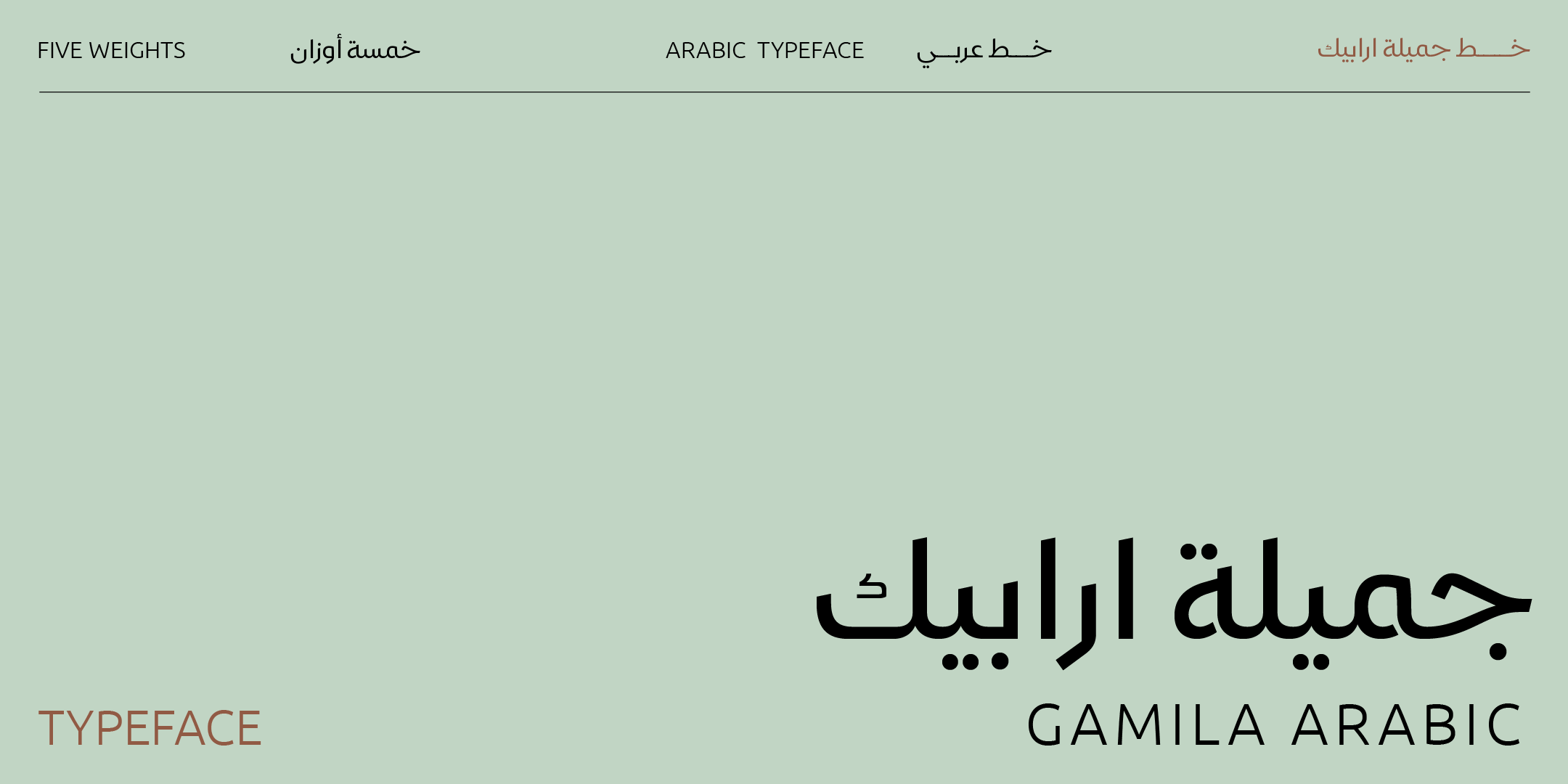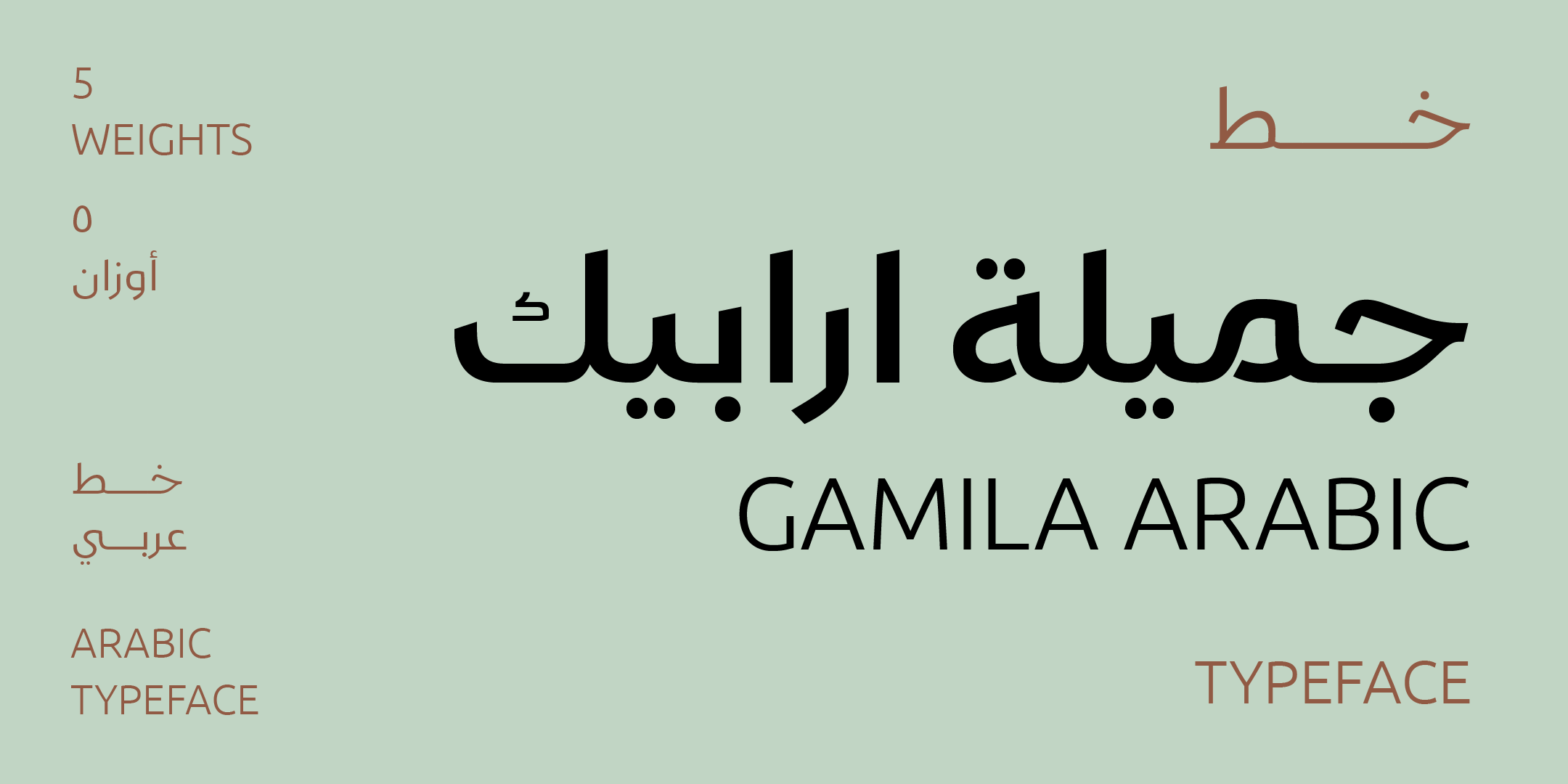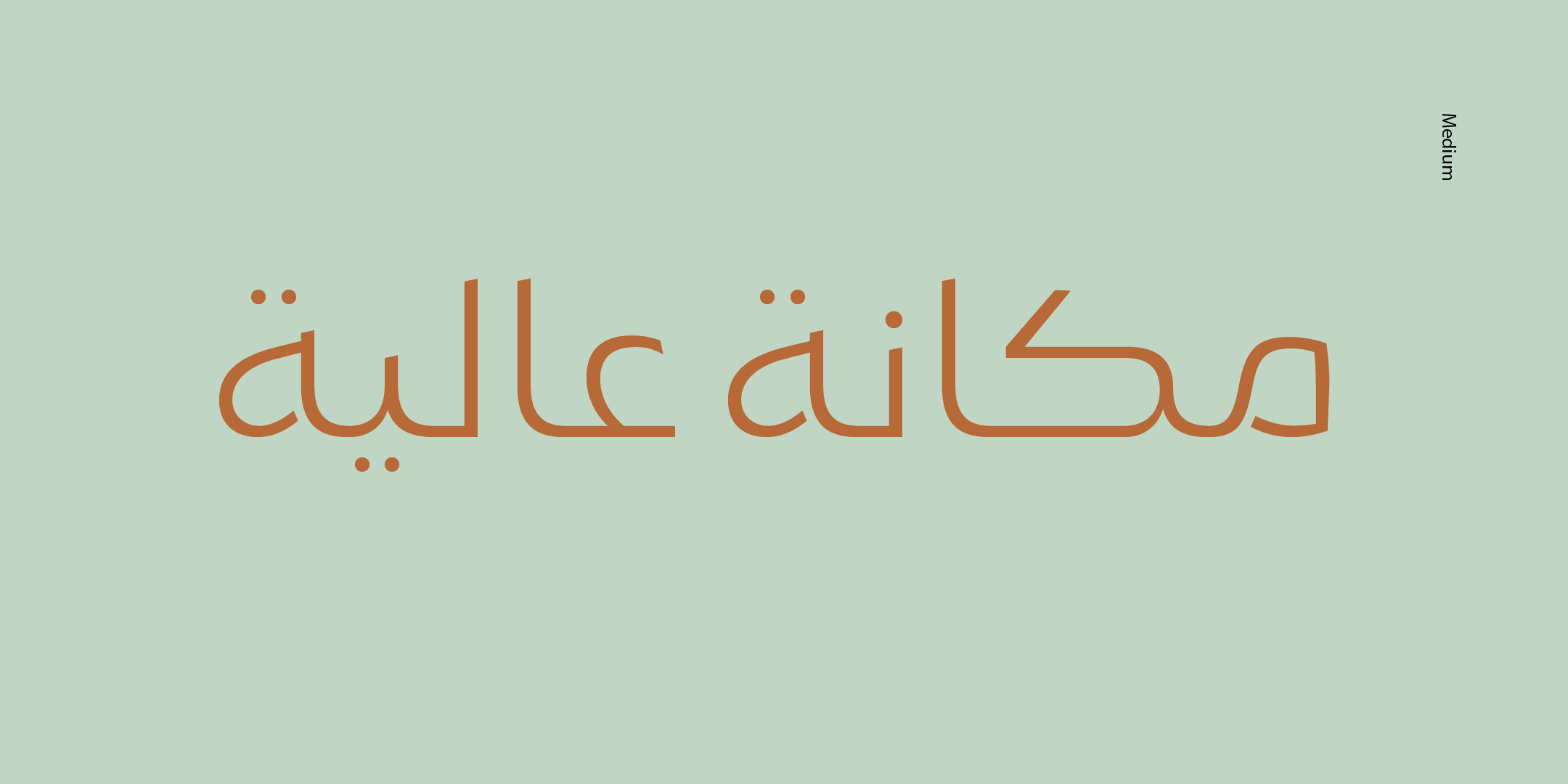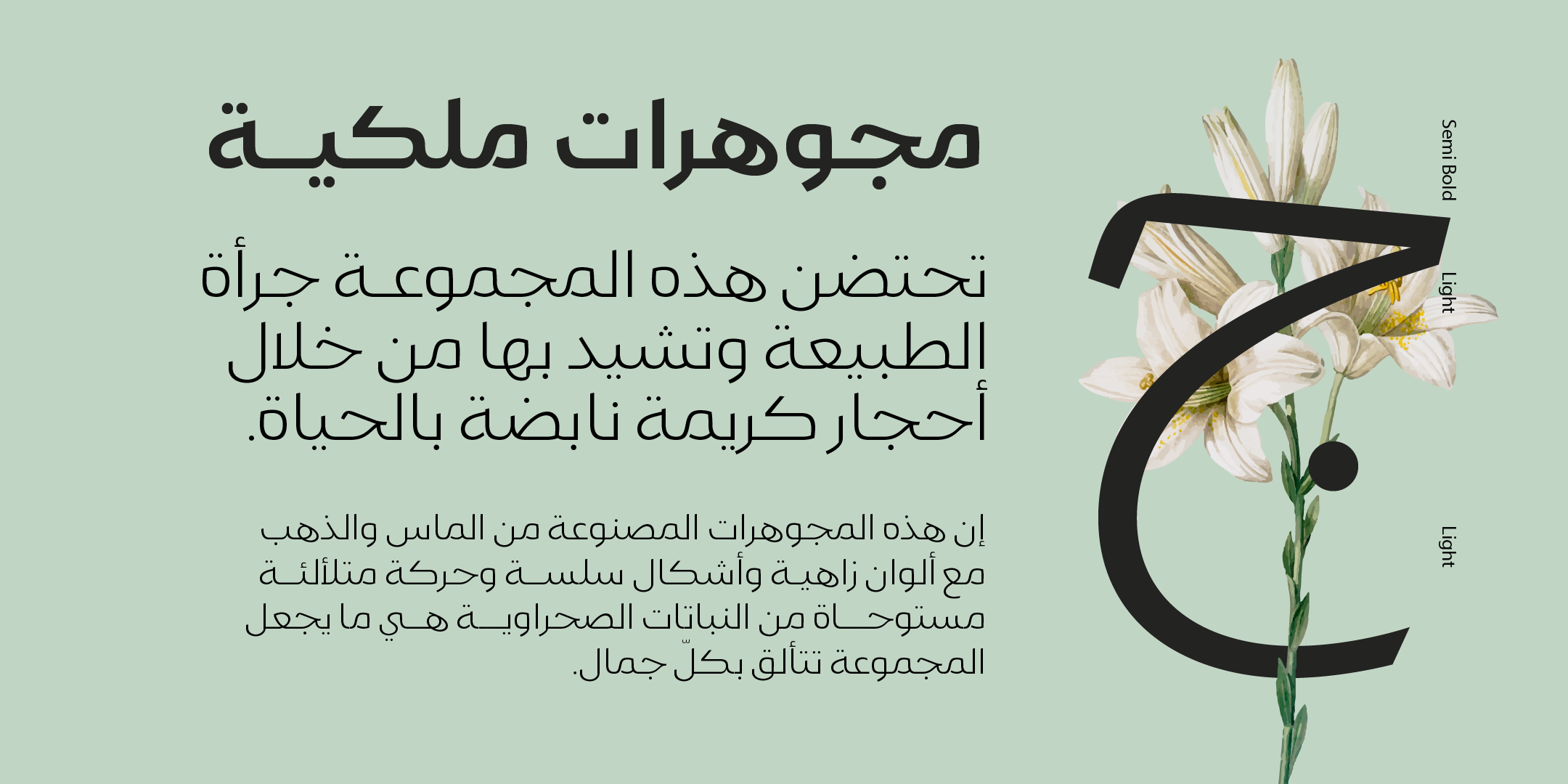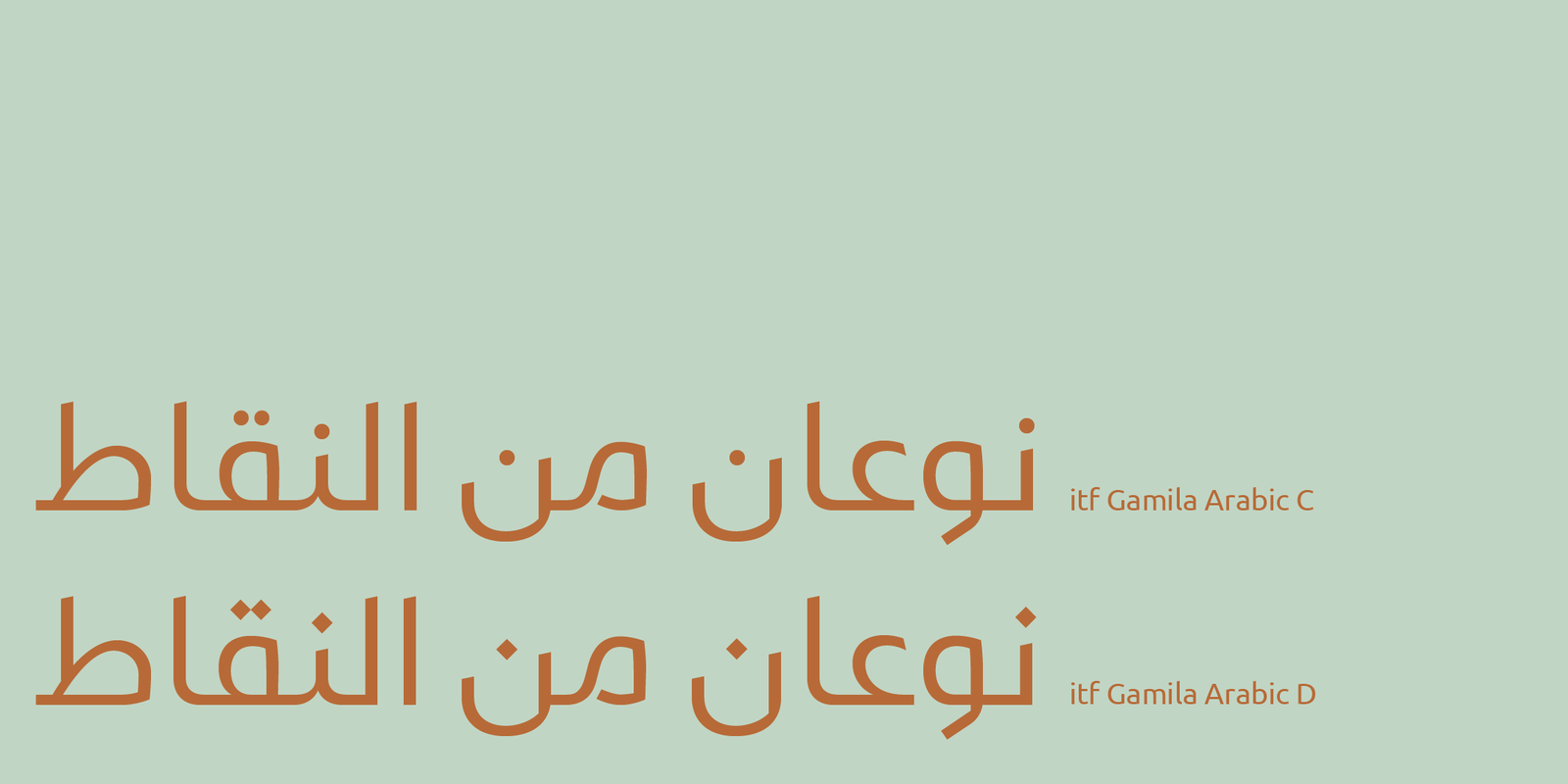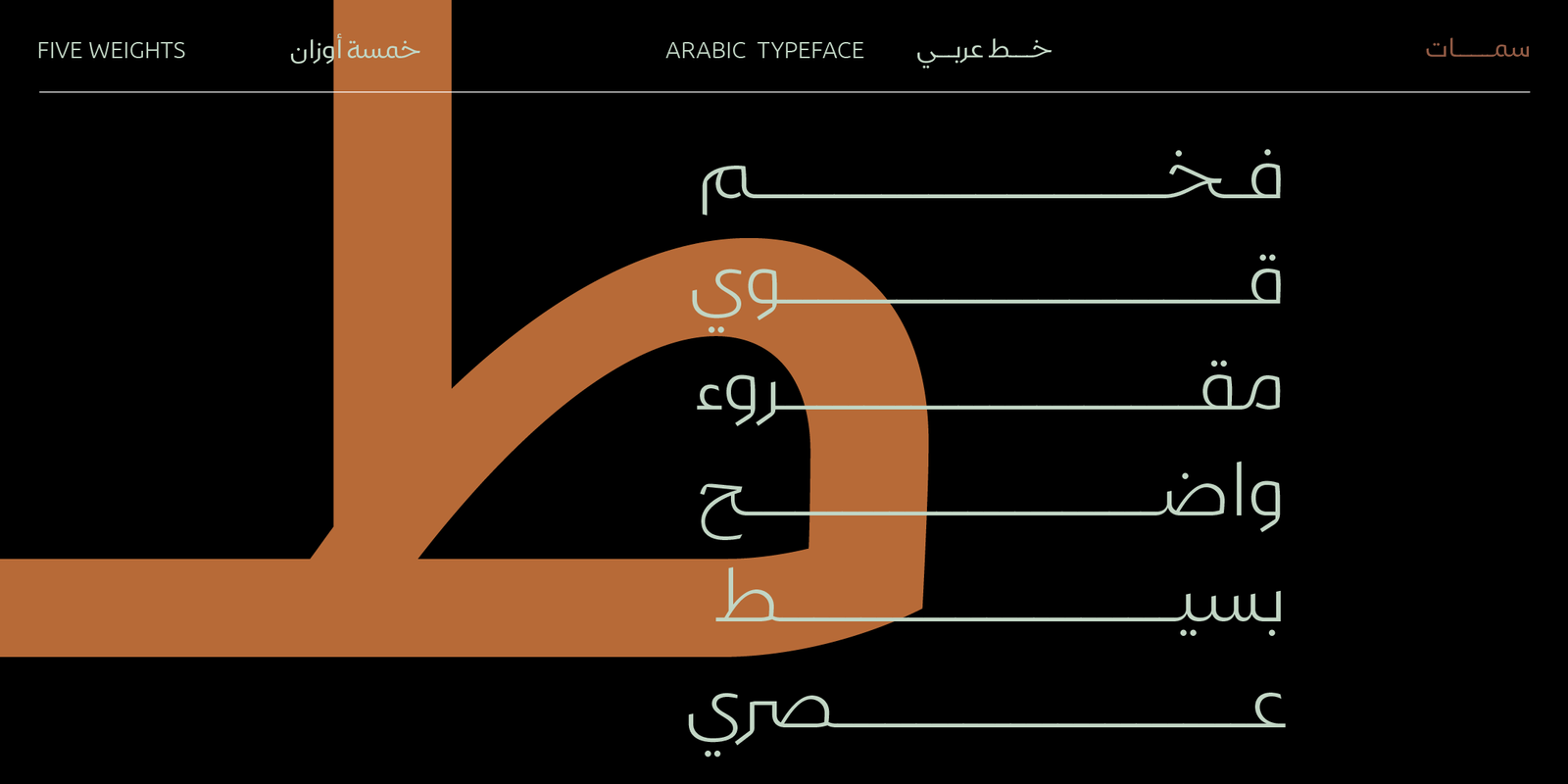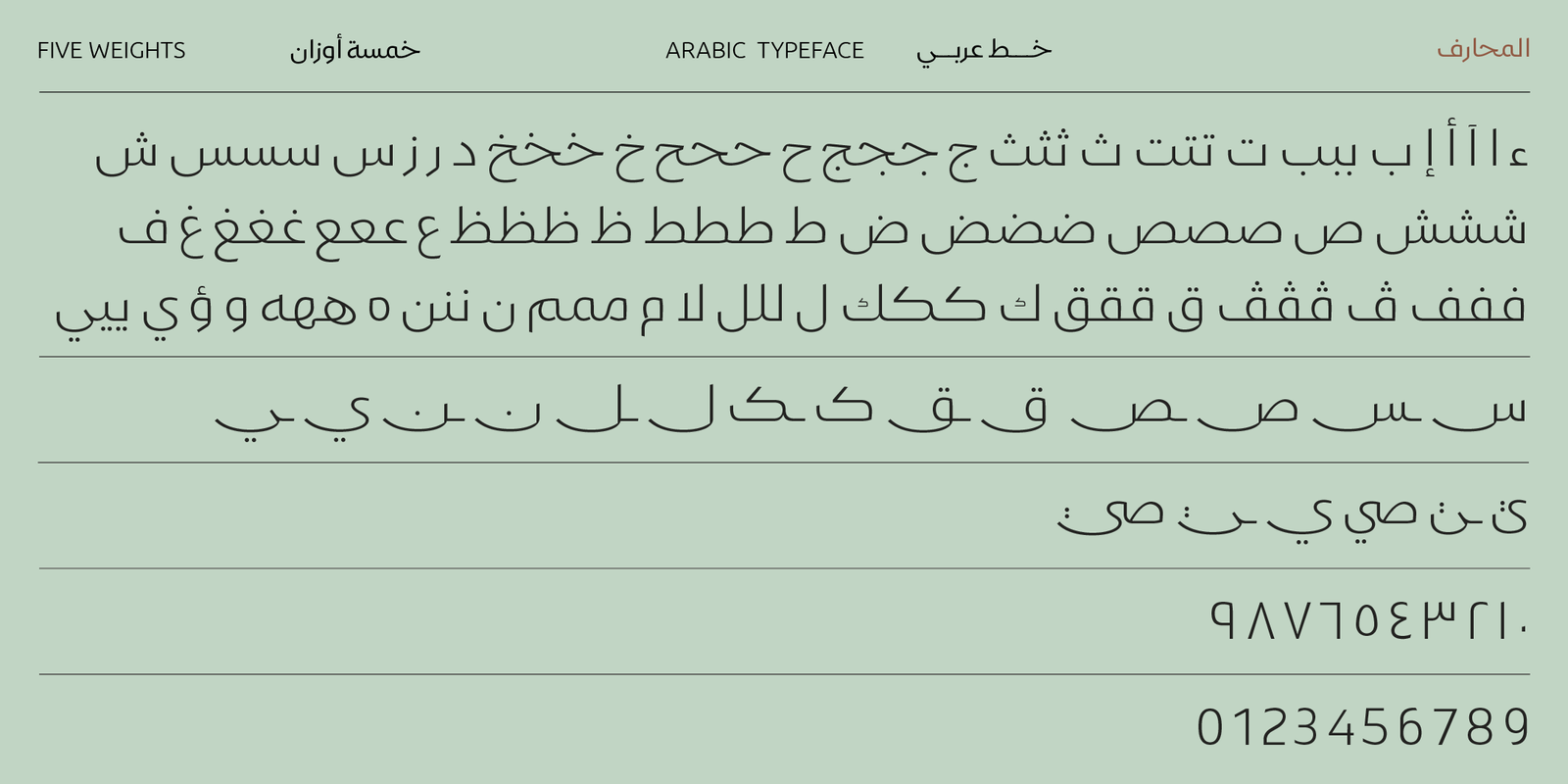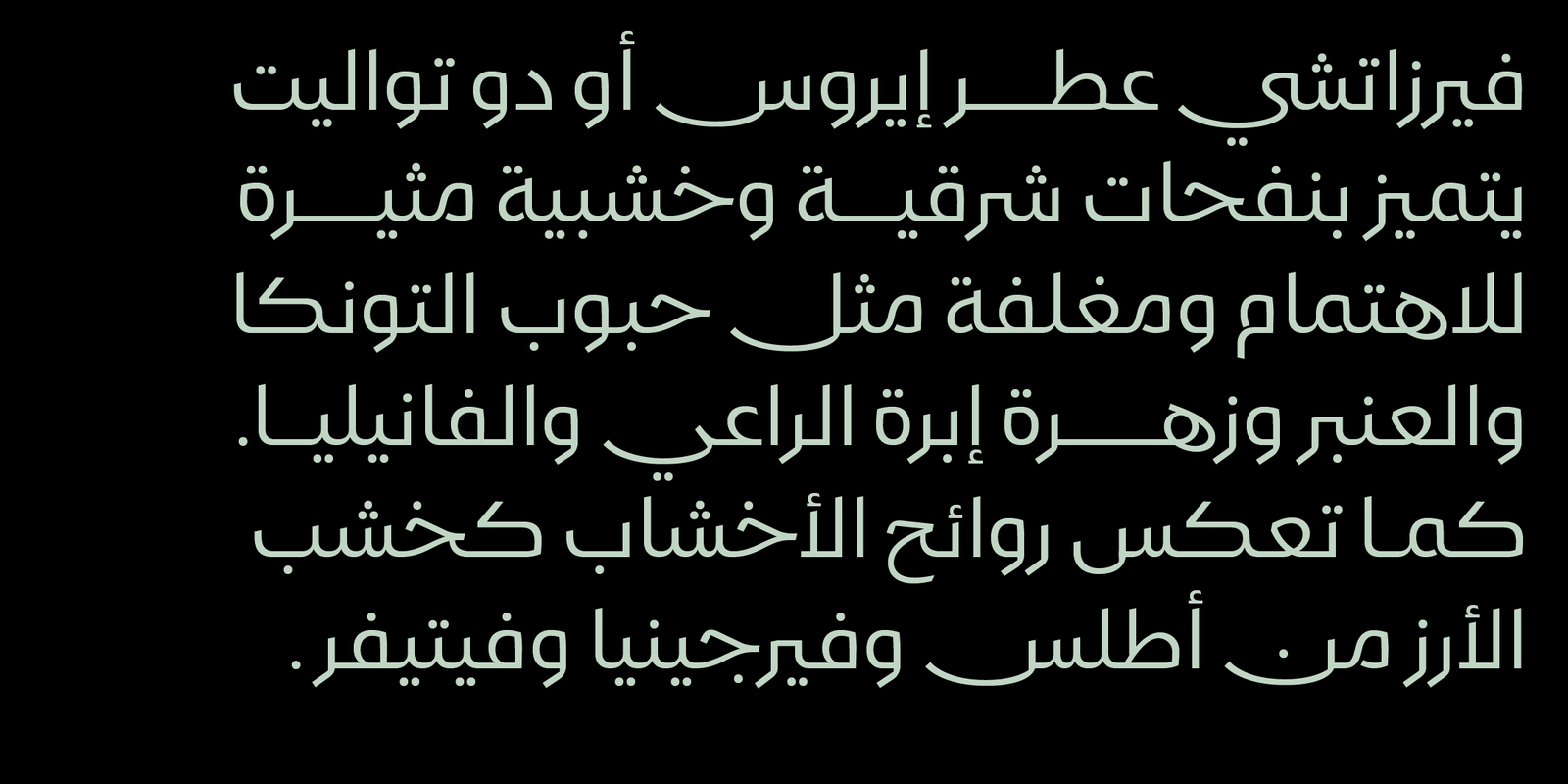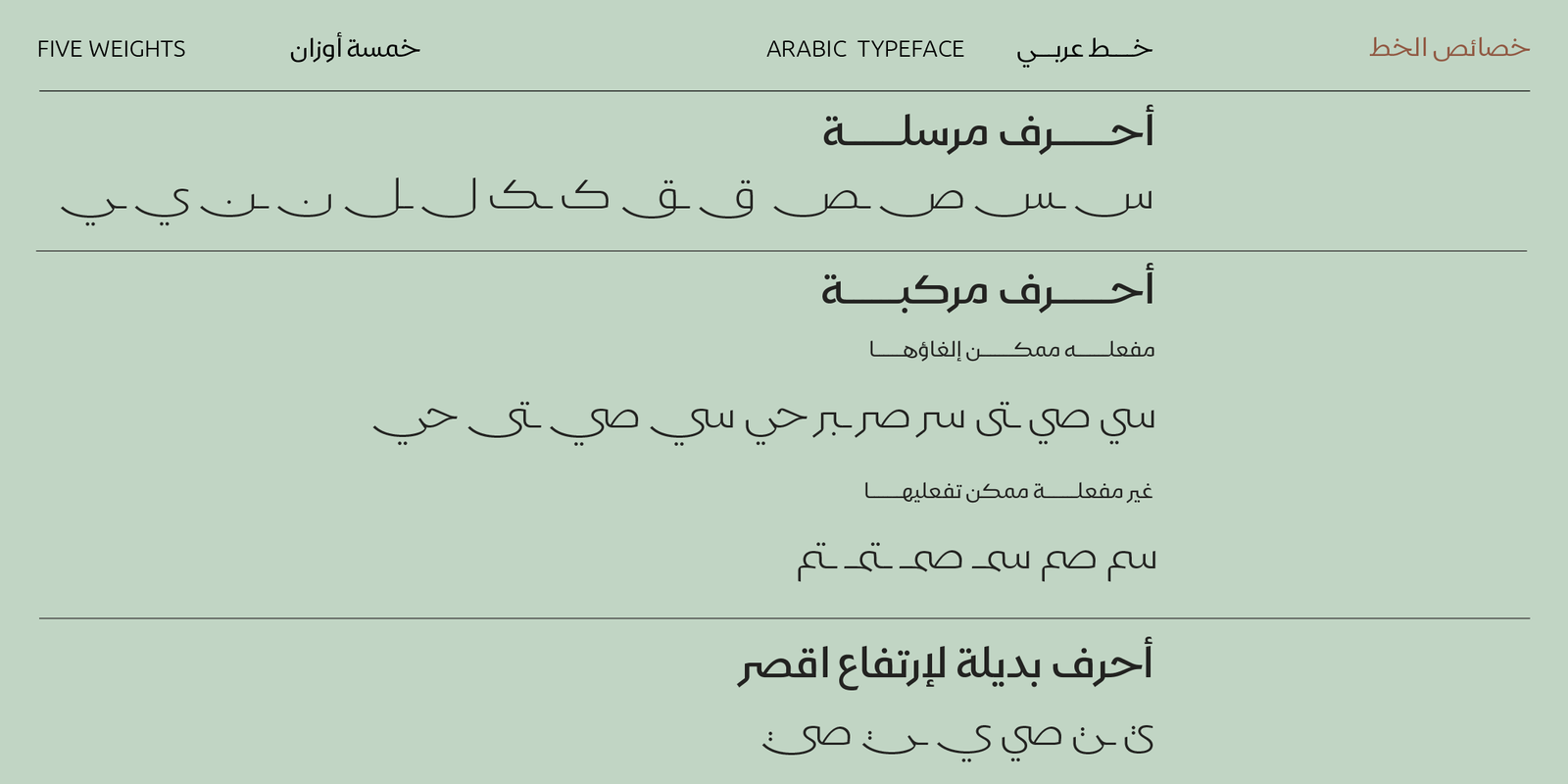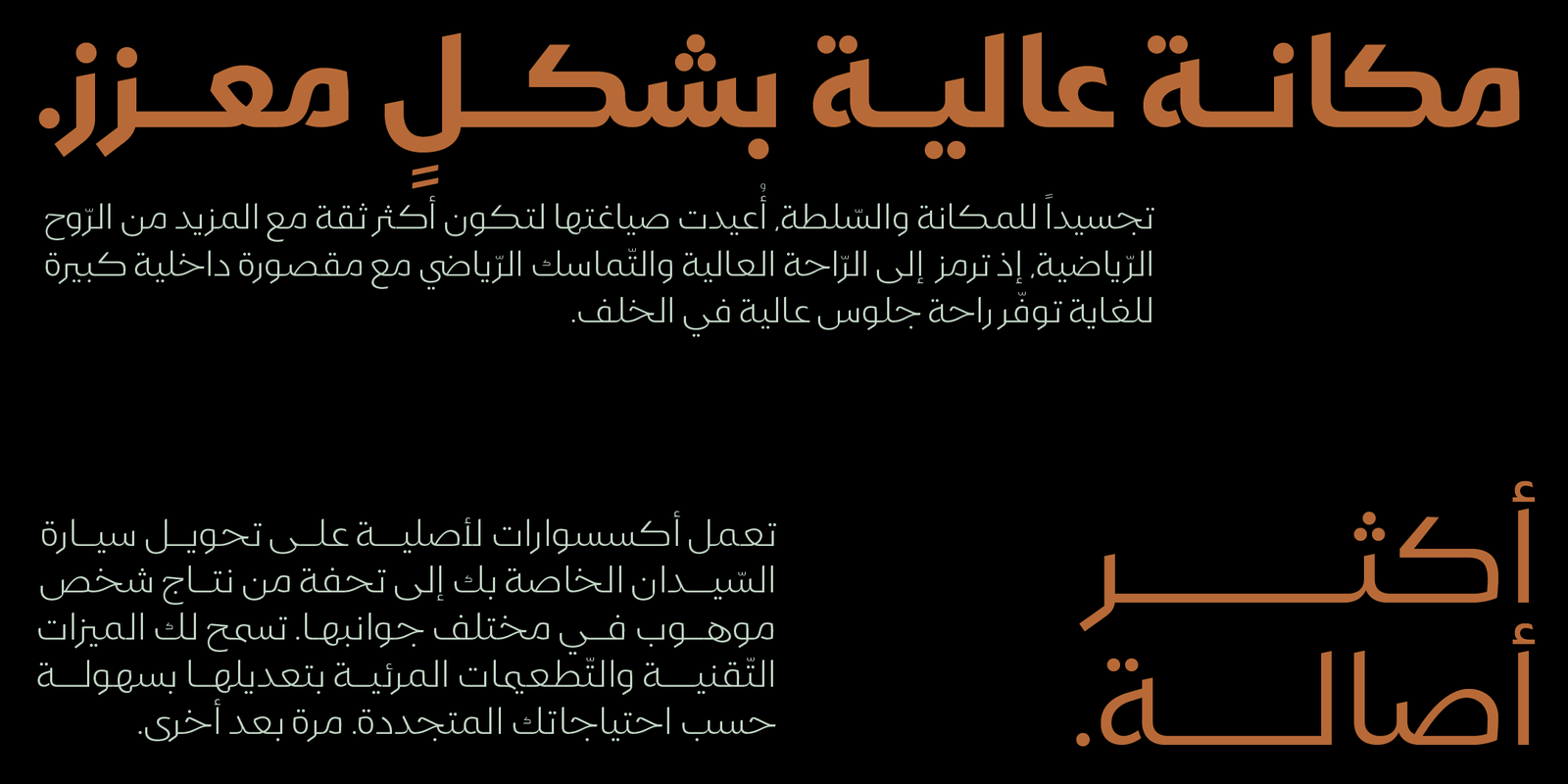
Gamila Arabic typeface – خط جميلة ارابيك
خط «جميلة» خط عربي معاصر أنيق، بتباين منخفض ونهايات حادة نظيفة، وأحرف مرسلة تمنح النص طابعا فاخرا. يناسب الهويات الراقية وأغلفة الكتب والتغليف والعناوين.
مميزات خط جميلة:
يتضمن الخط العديد من مزايا OpenType التي تضفي عليه مرونة وتنوعا في الاستخدام، مثل:
- نوعان من النقاط: دائرية وماسية، كل نوع في خط منفصل.
- أحرف مرسلة من خيار Stylistic Set 1.
- حرف ياء بنزول أقل.
- أحرف مركبة تحسن سلاسة التراكيب.
الأوزان: 5 أوزان